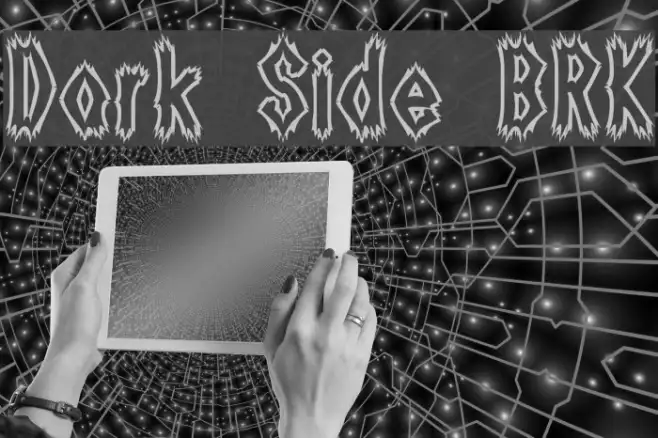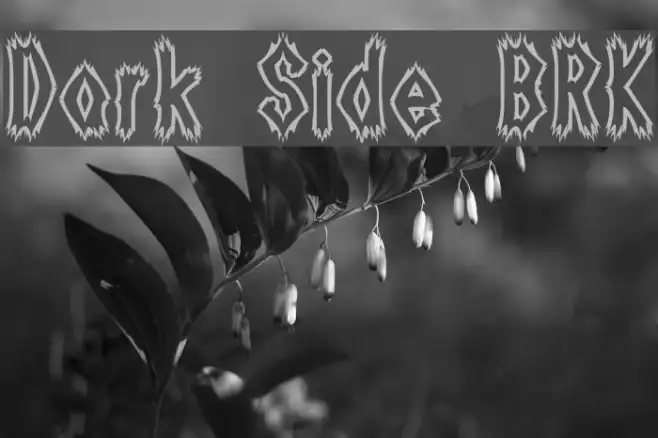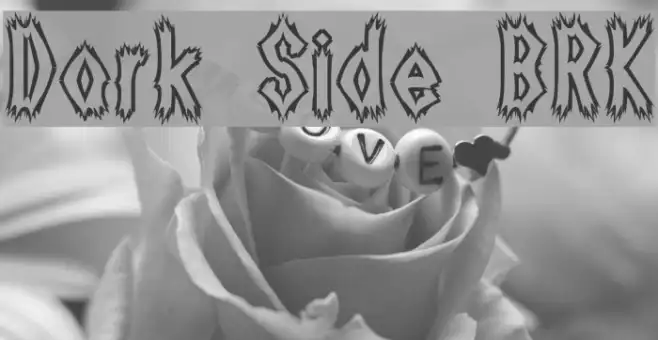
Dark Side [BRK] Font
| Kategorien | Outline |
| Anwendungsfall | Headlines, Posters, Branding |
| Vorgeschlagene Projekte | Ideal for horror-themed posters, Halloween invitations, edgy branding, or any project needing a dramatic flair. |